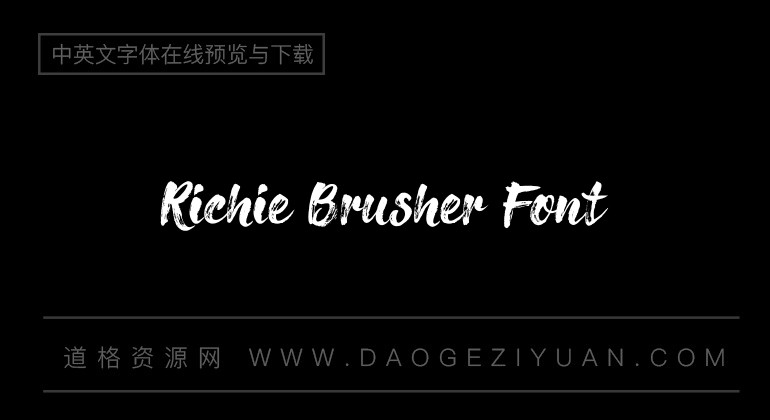
Richie Brusher Font是一种手写风格的字体,具有动感和个性。它有一种随意的笔画,仿佛是手绘的效果,让人感觉很自然和亲切。此字体的设计师是来自印度的Richie Mokhsein,他在设计这款字体时注意到传统字体的严谨和规矩,便想要创造一款更加自由和随意的字体。该字体适合用于海报、标志、印刷品和其他设计项目,可以带来一种独特的视觉效果。内容介绍
Richie Brusher Font是一款非常不错的手写艺术字体,具有很好的视觉感,适合于文化类的宣传设计、商业类品牌的广告和产品包装设计以及个性化文字排版等较多场景。